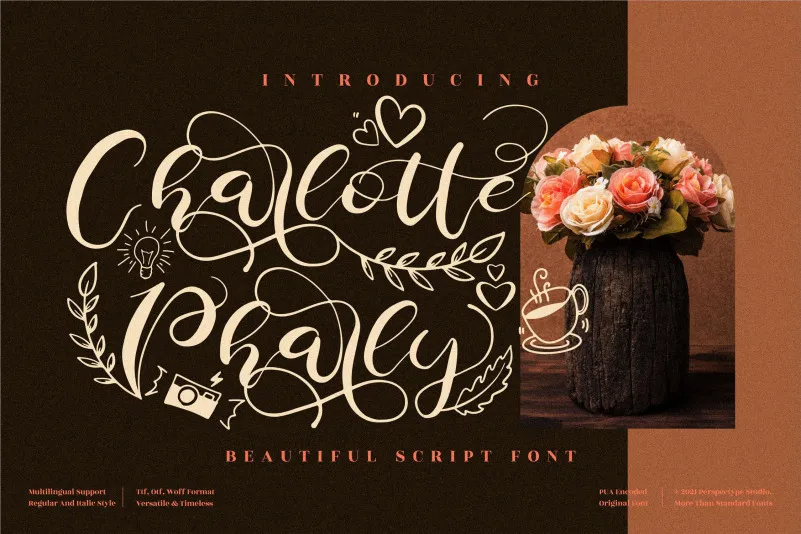
A Charlotte Pharly Font é uma opção perfeita para quem busca criatividade e sofisticação em seu design. Esta elegante e refinada fonte script pode ser usada para criar logotipos, marcas de marca, convites de festa, embalagens de cartão de papelaria, designs de casamentos e até mesmo postagens nas redes sociais. O PUA encoding da font permite que você facilmente aceda a todos os caracteres e swashes disponíveis, oferecendo-lhe uma gama incrível de opções. Esta font é um verdadeiro trunfo para qualquer projeto visual, garantindo elegância e modernidade em cada detalhe. Engane-se se pensa que essa fonte é apenas para eventos formais – ela também está perfeitamente equipada para adicionar personalidade ao design de blogs pessoais ou sites de moda. Em resumo, a Charlotte Pharly Font é uma escolha inteligente para aqueles que buscam qualidade e criatividade em cada letra do seu próximo projeto visual.